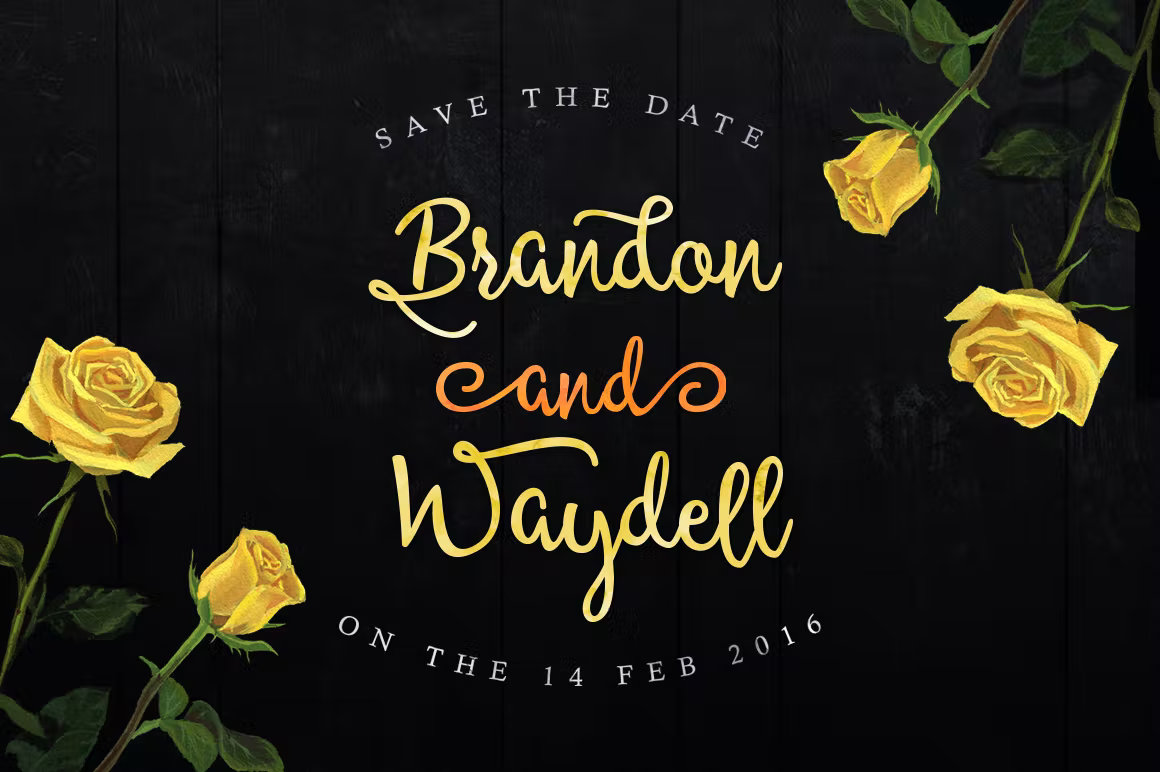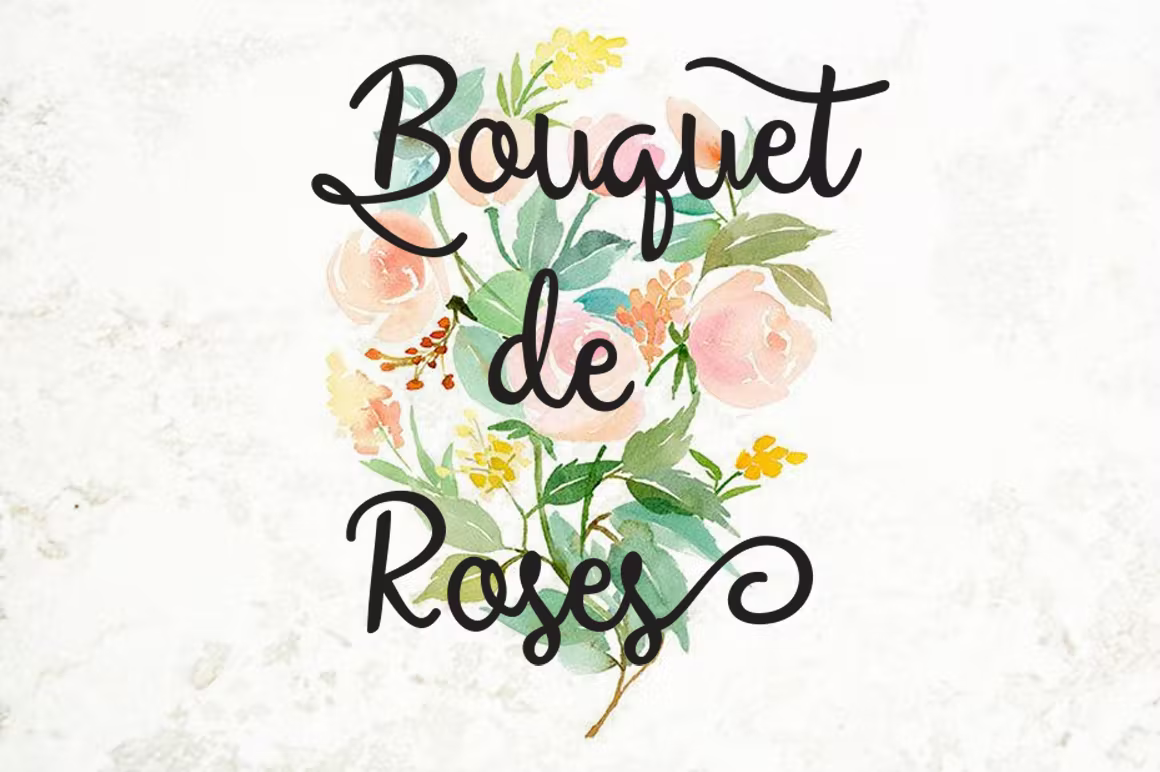
Allessa Script Font
Description de Allessa Script Font
Allessa Script est une belle écriture faite à la main qui donne un aspect naturel. 312 glyphes et caractères alternatifs contiennent des fonctionnalités de type ouvert. Alternatives stylistiques, Ligature, Swash et plus encore. Vous pouvez accéder à tous ces caractères alternatifs en utilisant des programmes OpenType tels qu’Adobe Illustrator et Adobe InDesign.
Idéal pour les marques de vêtements, les cartes de vœux, les couvertures de livres, les styles de peinture ou tout design nécessitant une touche naturelle et personnelle. Mélangez et associez les personnages alternatifs pour ajouter un message attrayant à votre design.